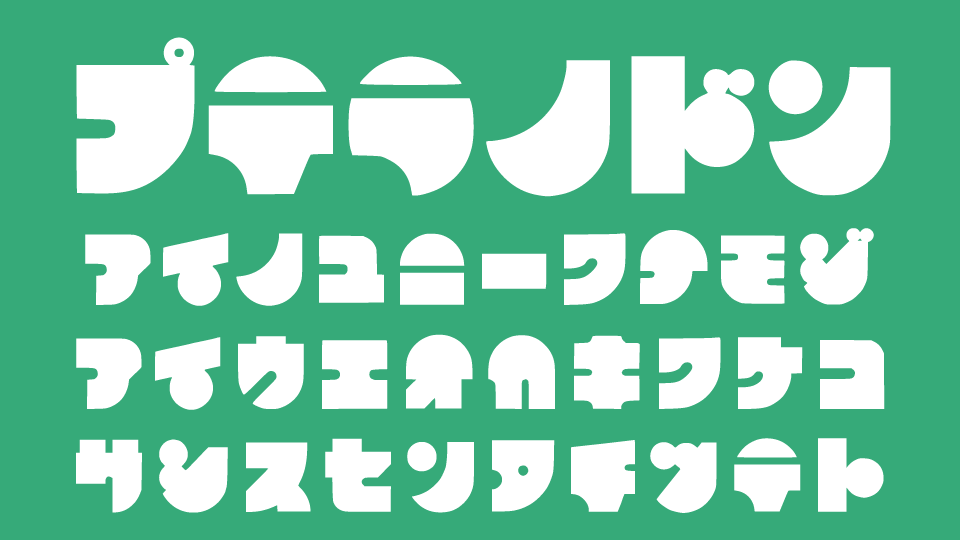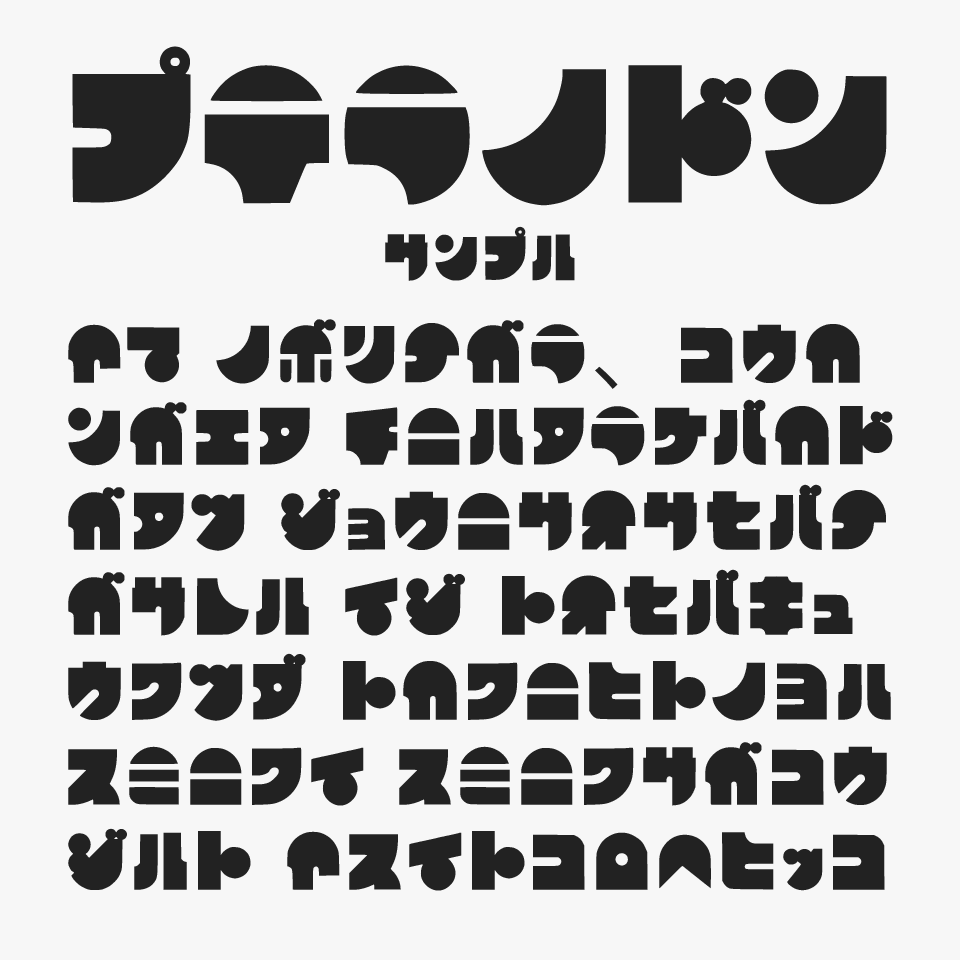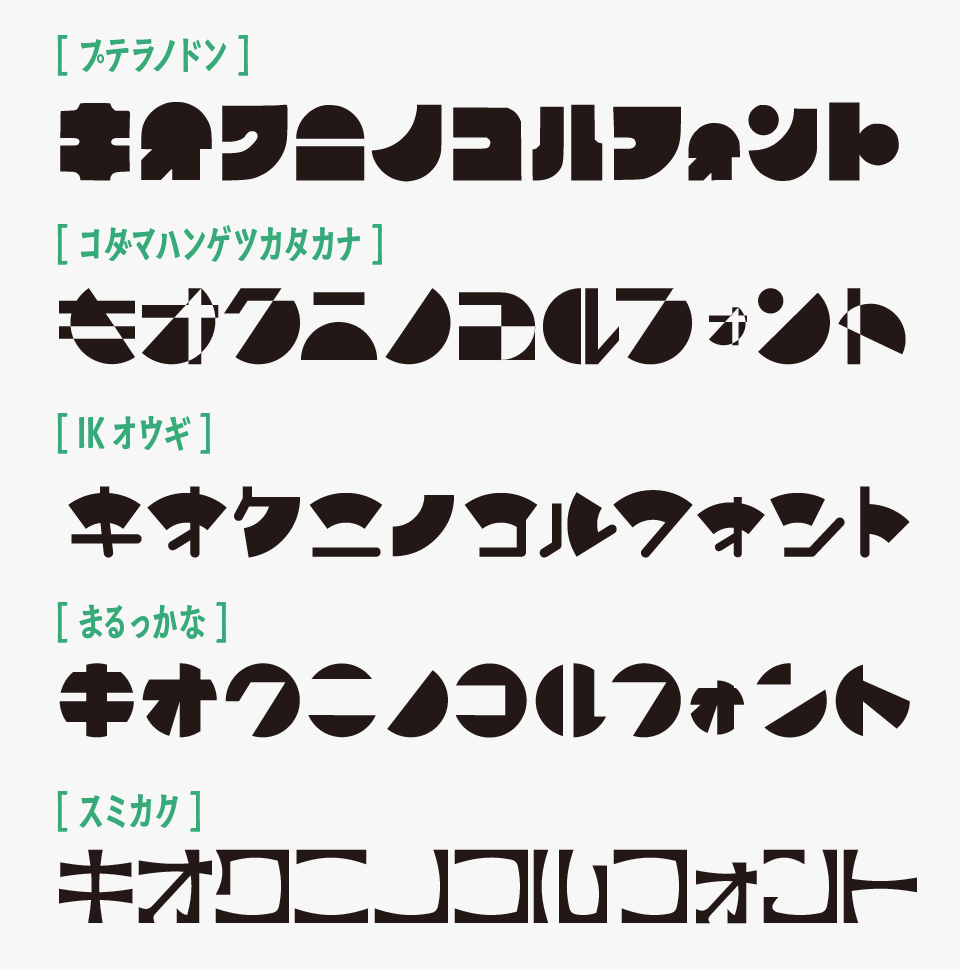
プテラノドンフォントは、幾何学的なパーツを大胆に組み合わせた、おもちゃのような遊び心がたっぷりのデザインカタカナフォントです。
半円や直線を大胆に切り分けた独特の字形によって、まるでロゴのようなインパクトあるフォントです。文字の中にリズムよく配置された丸いアクセントも特徴で、無機質になりすぎない遊び心が感じられるフォントです。
どこか懐かしいレトロっぽい雰囲気も感じられます。
プテラノドン
プテラノドンフォントは、ほかの幾何学的な雰囲気を持つフォントと比較してみると、極太で強いインパクトがありながらも、視認性の高さがしっかり保たれているところが魅力です。
比較フォントは「コダマハンゲツカタカナ」「IKオウギ」「まるっかな」「スミカク」を使用していますが、どのフォントもとても可愛らしさがあるので、あわせてチェックしてみてください。
プテラノドンフォントと、「コダマハンゲツカタカナ」「IKオウギ」「まるっかな」「スミカク」を比較